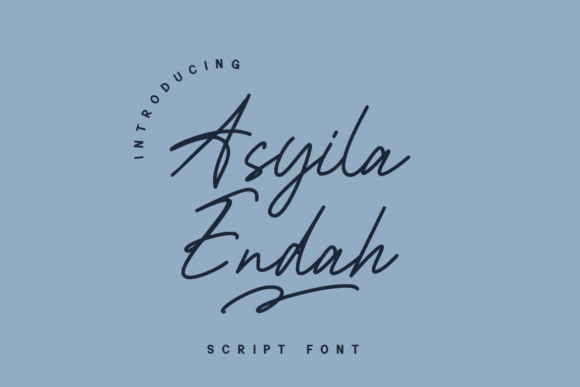
Asyila Endah
Trouver les bons éléments de conception peut être un défi, mais Asyila Endah propose une collection exceptionnelle qui rehausse instantanément votre travail.
Que vous créiez des produits POD (impression à la demande), des invitations de mariage ou des visuels pour les réseaux sociaux, Asyila Endah est un choix idéal.